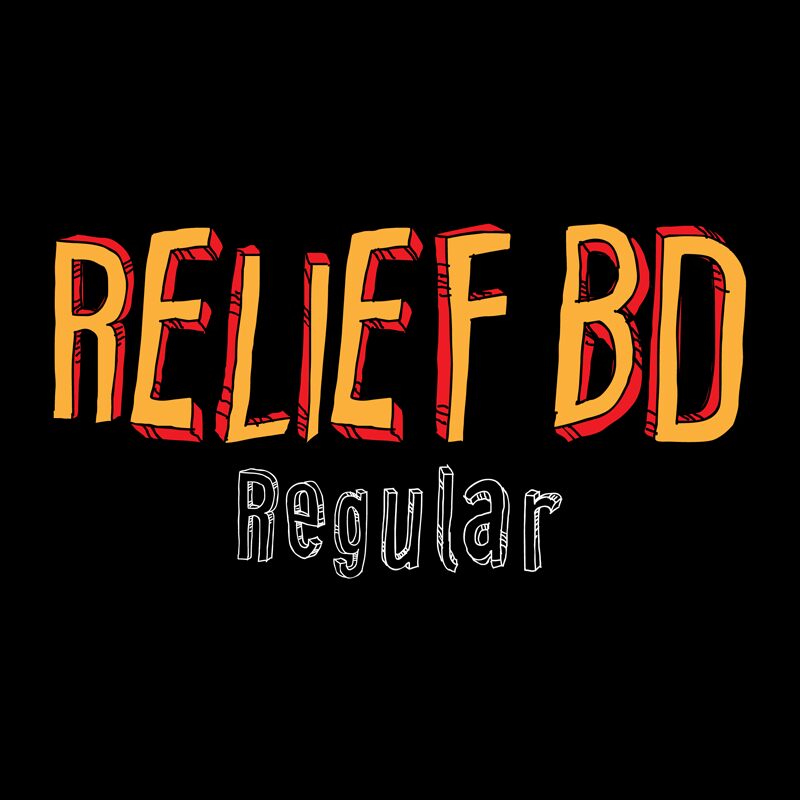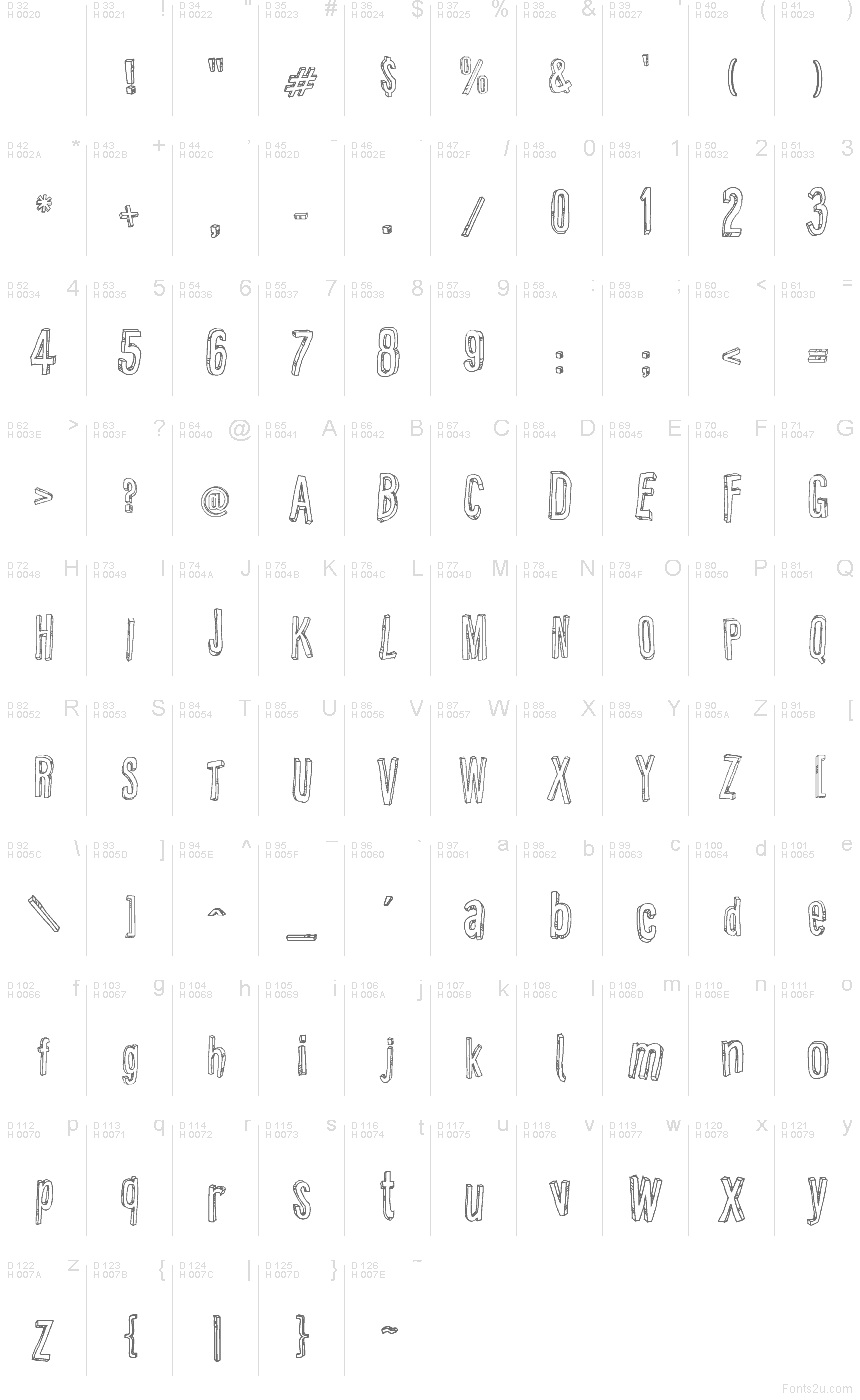
Relief BD Regular
Relief BD di Galdino Otten è un font 3D gratuito in stile cartoon con un carattere che richiama le lettere intagliate a mano. Le lettere appaiono volutamente cesellate e irregolari, con sottili striature interne e piani laterali inclinati che conferiscono al font una giocosa profondità in bassorilievo, evitando l'effetto digitale troppo piatto o levigato.
È ideale per poster, titoli in stile fumetto, packaging, copertine di libri per bambini, titoli video e flyer di eventi, dove il lettering deve trasmettere un tocco illustrativo. Essendo un font gratuito, rende al meglio in contesti di visualizzazione brevi, specialmente per grandi nomi o copertine, dove i bordi peculiari e le ombre interne sembrano più lettere disegnate a mano che un carattere tipografico neutro.